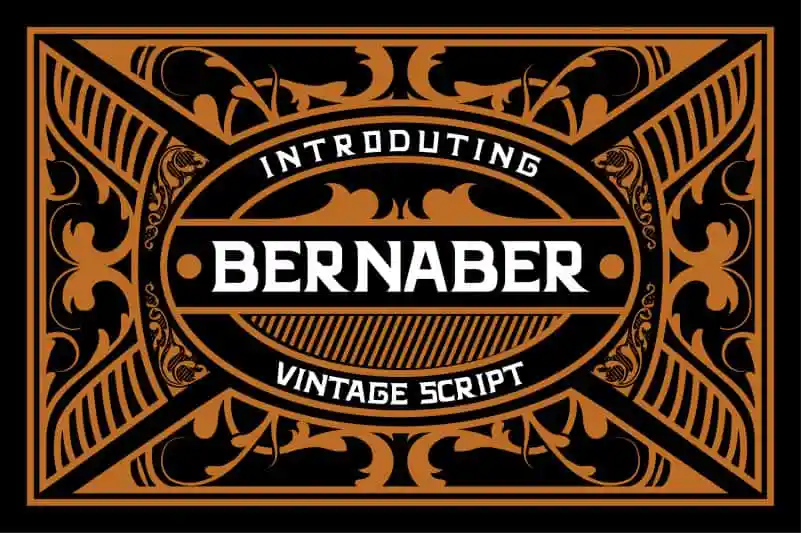
Bernaber Display Font – Download Grátis
Introduzimos Bernaber Display Font, uma nova opção para quem busca um estilo forte e vintage no seu design. Esta fonte de display foi criada pelo kntypeco, e se adapta perfeitamente a uma variedade de projetos visuais. É ideal para aplicativos de cartão, e-card, logotipos e headlines. Além disso, sua elegância torna-a um recurso valioso para design de outdoors, selos, anúncios em jornais e revistas. A Bernaber Display Font é uma escolha ótima para trazer vida e ação aos seus projetos gráficos. Experimente incorporar esta fonte a suas criações e veja o impacto que ela pode ter!